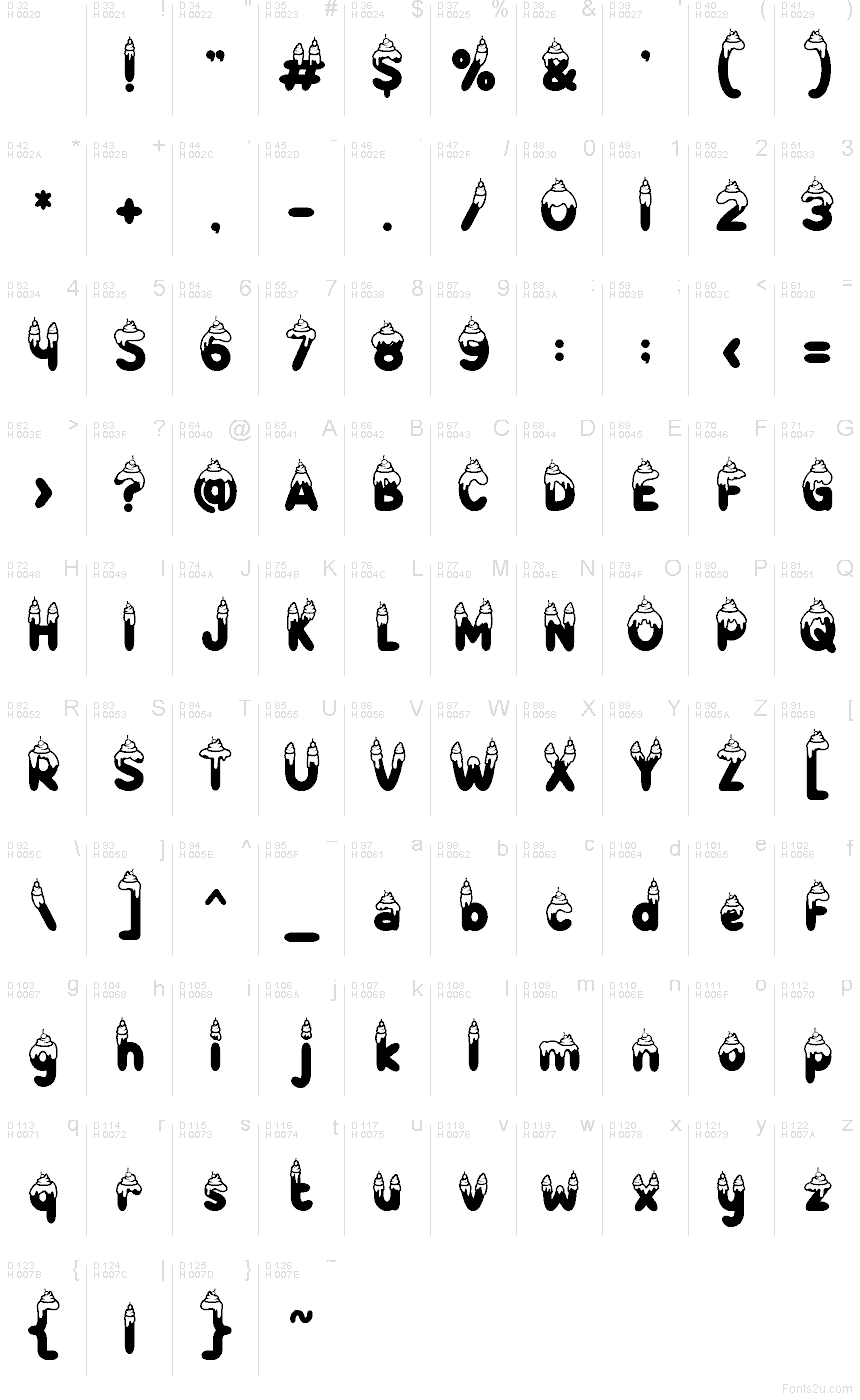
Cake Couture Nine
Cake Couture Nine von Putracetol Studio ist eine kostenlose Display-Schriftart im tropfenden Glasur-Look mit echtem Cartoon-Bäckerei-Charme. Die Buchstaben wirken dick, rund und leicht cremig; jeder einzelne ist mit einem Spritzglasur-Effekt versehen, sodass das gesamte Alphabet eher wie frisch garniert als nur beschriftet aussieht.
Sie passt perfekt zu Logos für Bäckereien, Geburtstagseinladungen, Verpackungsdesign für Torten, Party-Postern und süßen Social-Media-Beiträgen, bei denen eine kostenlose Schrift mit einem originellen „essbaren“ Look sofort ins Auge sticht. Nutzen Sie sie für kurze Namen, Cover, Titel oder Menüüberschriften – besonders dann, wenn die Schrift so aussehen soll, als käme sie direkt aus dem Spritzbeutel statt aus der Feder.